10 Font Canva yang Bagus untuk Desain hingga Slide Presentasi
Dalam membuat desain maupun slide presentasi, pemilihan font jadi faktor penting yang harus diperhatikan. Pasalnya, font yang kamu pilih dapat memberikan pengaruh besar pada orang yang membaca. Oleh karena itu, kamu perlu menerapkan font yang bukan hanya bagus, tapi juga mudah dibaca dan sesuai konteks pembahasan.
Berikut ada font Canva yang bagus dan bisa kamu manfaatkan untuk berbagai desain hingga slide presentasi. Gak membosankan, tetapi juga gak berlebihan sehingga membuat orang lain lelah membacanya. Jadi betah mantenginnya, deh.
Font Canva yang bagus
FYI, font atau bentuk huruf yang digunakan dalam tulisan dapat bersifat multi sensorik, melansir Penji. Itu berarti font dapat memengaruhi lebih dari satu indra. Font pun dapat membangkitkan emosi, bahkan walau hanya melihat bentuknya tanpa membaca isinya.
Sepenting itu, makanya pemilihan font gak bisa sembarangan. Alih-alih mencari dari sekian banyak font yang ada di Canva, berikut beberapa rangkuman font yang bisa digunakan.
1. Kingred Modern
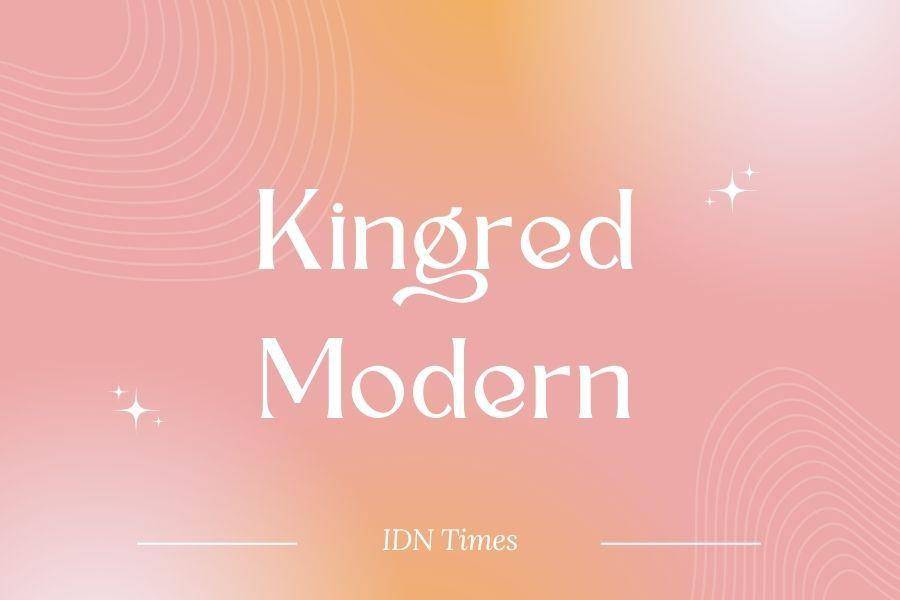
ilustrasi font Canva (dok. Canva) Mencari tulisan yang cocok untuk heading, tapi ada sentuhan artistik? Kingred Modern bisa jadi pilihan pas. Font ini memiliki lekukan ala vintage dengan basis serif.
Font ini cocok digunakan ketika kamu sedang membuat desain yang klasik. Gak membosankan, tapi tetap bisa terbaca dengan jelas.
2. Signature
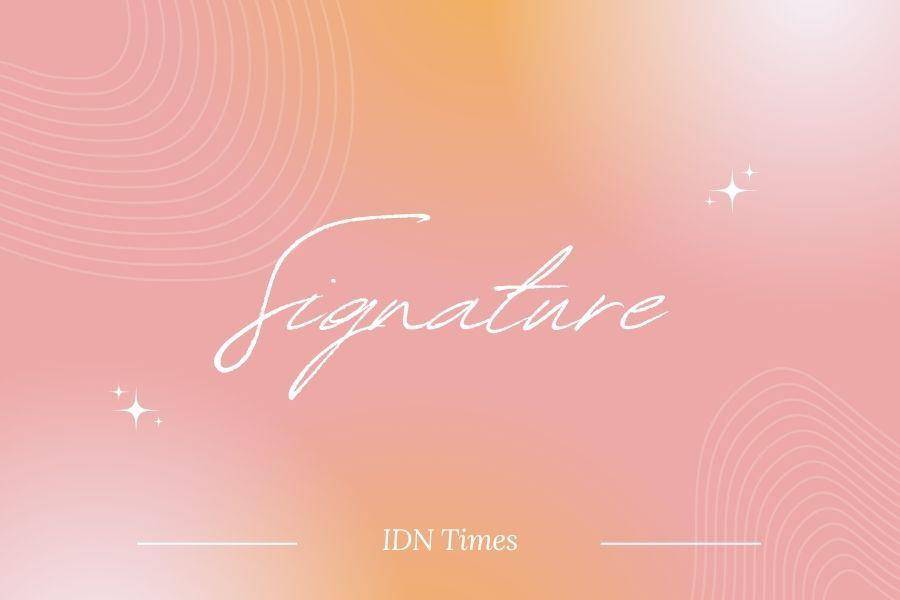
ilustrasi font Canva (dok. Canva) Font Canva yang bagus untuk desain dan slide presentasi berikutnya ada Signature. Sesuai namanya, font ini seperti handwritten yang menyerupai tanda tangan.
Signature mungkin tidak terlalu jelas terbaca jika digunakan untuk font head atau judul. Namun, font ini sangat cocok menjadi highlight dan dikombinasikan dengan font geometris dalam kontenmu.
3. Balgin
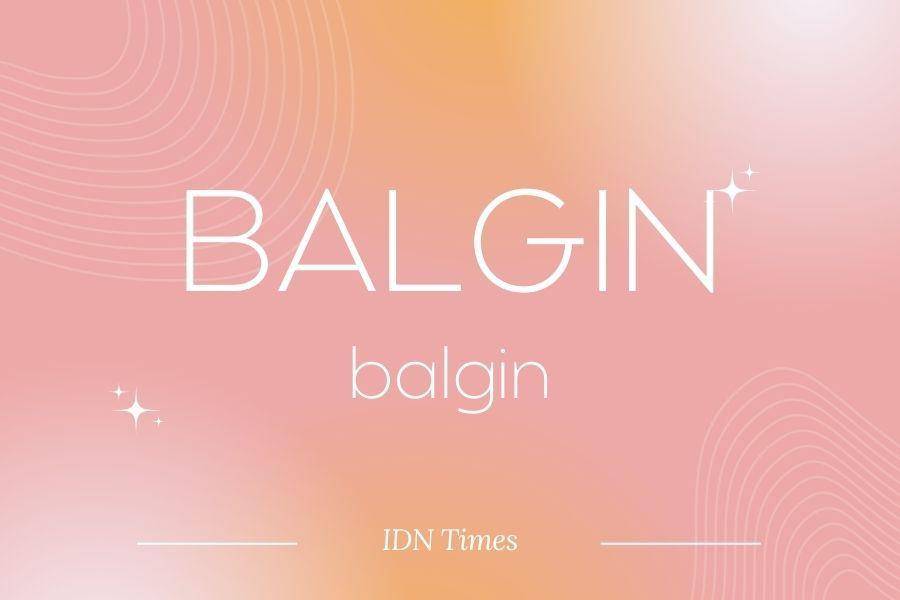
ilustrasi font Canva (dok. Canva) Mencari font Canva yang bagus dan tegas, tanpa harus memberikan penekanan? Gunakan font Balgin untuk atensi utama dalam desainmu. Meski terkesan masif, font ini gak memberikan aksen intimidatif.
Huruf ini menggunakan garis tajam dan struktur yang bersih. Pas juga digunakan untuk sentuhan retro. Desainmu pun makin estetik dan jelas.
4. Tan Meringue
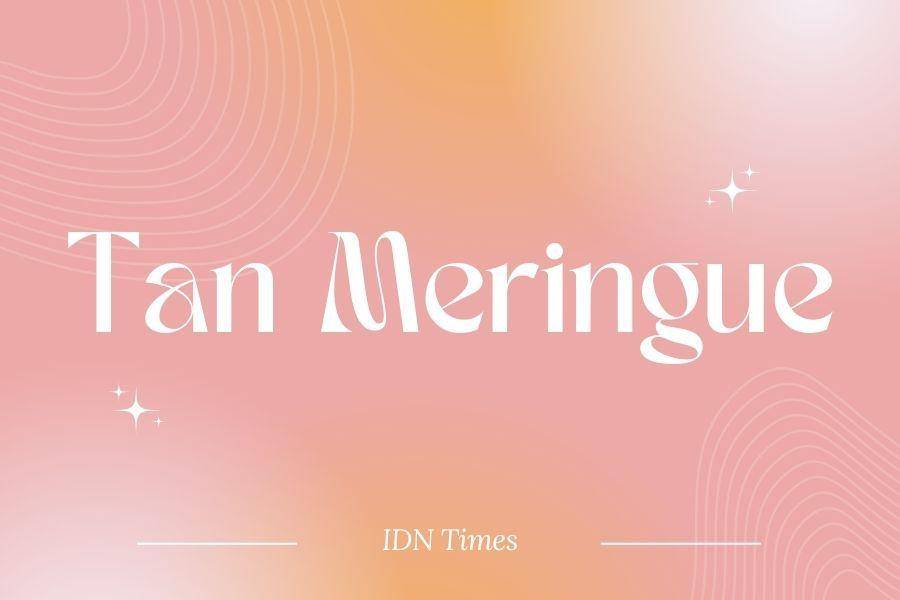
ilustrasi font Canva (dok. Canva) Tan Meringue merupakan font yang dibuat oleh tim kreatif TanType. Mengusung konsep retro, karakter dari font ini memiliki sentuhan yang gak sepenuhnya kaku, tapi tetap mudah dibaca.
Font ini mendukung huruf kapital maupun huruf kecil. Kombinasi keduanya pun tetap menghasilkan display tulisan yang aesthetic.
5. Gistesy
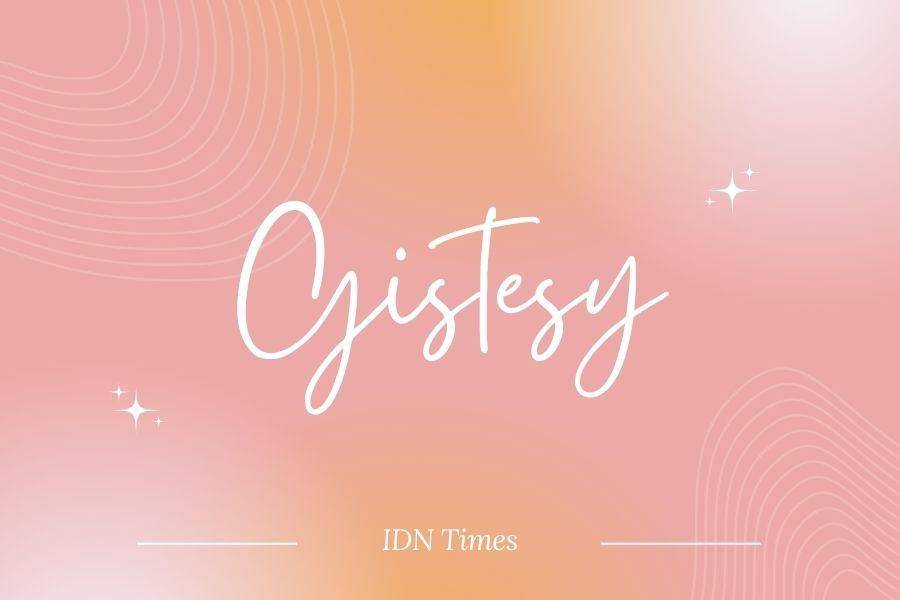
ilustrasi font Canva (dok. Canva) Gistesy merupakan handwritten font yang menampilkan kesan ceria. Meski merupakan huruf bersambung, fon ini masih tetap mudah terbaca. Cocok untuk dibuat heading maupun highlight tambahan di desainmu.
Fon ini tetap cocok berdiri sendiri, jika konsep desainnya informal. Kamu pun bisa memadukannya dengan huruf geometris jika digunakan sebagai aksen tambahan.
6. Julius Sans One
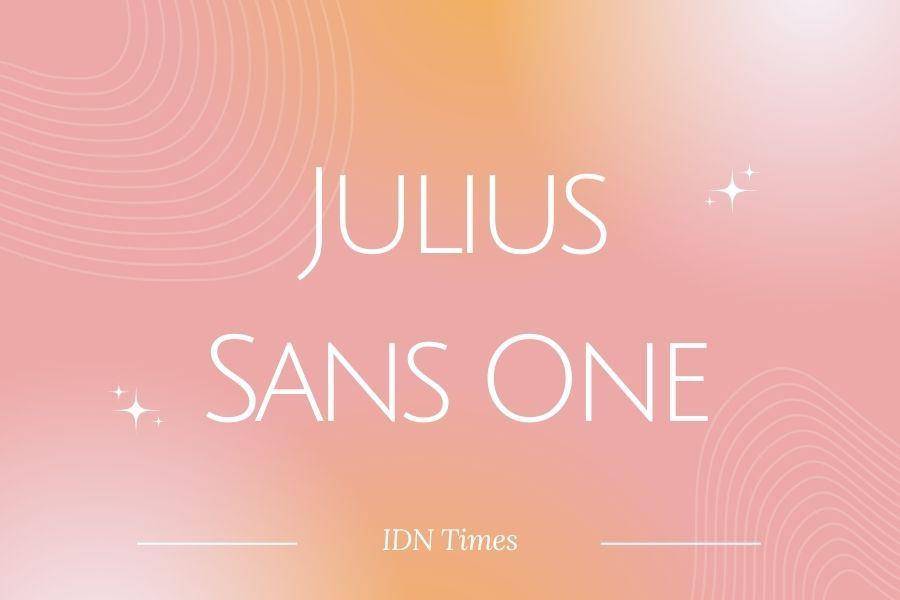
Mencari font Canva yang bagus untuk desain, slide presentasi, bahkan untuk desain branding merekmu? Julius Sans One merupakan satu fon yang bisa all in one. Modelnya sederhana, tetapi gak membosankan.
Kamu pun dapat mengatur tingkat kerapatan antar huruf. Memberikan kesan tegas, mudah terbaca, tanpa harus terkesan kaku.
7. Hatton
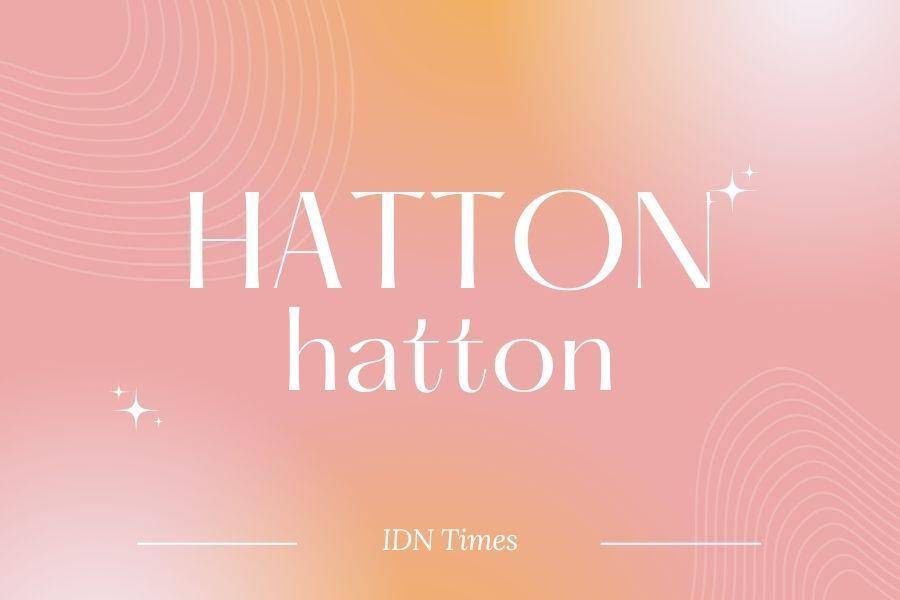
Font Canva yang bagus untuk desain sampai slide presentasi berikutnya bernama Hatton. Fon ini termasuk jenis huruf kaligrafi. Perancangnya adalah Mathieu Desjardins yang bekerja sama dengan studio desain Two Times Elliott.
FYI, desain font ini terinspirasi dari rambu jalan dan bagian depan toko listrik di distrik Hatton Garden, London. Kamu bisa menggunakannya sebagai huruf kapital dengan aksen maupun huruf kecil.
8. Sego
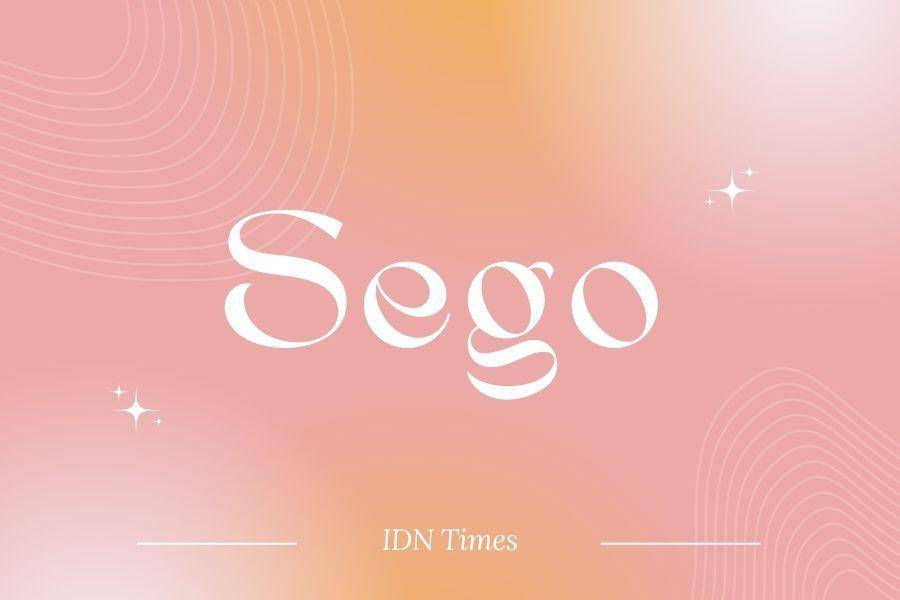
Font Sego merupakan bentuk huruf serif dengan sentuhan elegan dan modern. Tiap hurufnya memiliki akses dan lekukan yang berbeda. Bukan hanya itu, ada beberapa font alternatif yang bisa bikin desain makin ciamik.
Bentuk font yang menarik, membuatnya cocok diaplikasikan untuk banyak hal. Karakter yang dibangun dari font ini pun kuat sehingga membuat desain tampak lebih hidup.
9. Josephine Sans
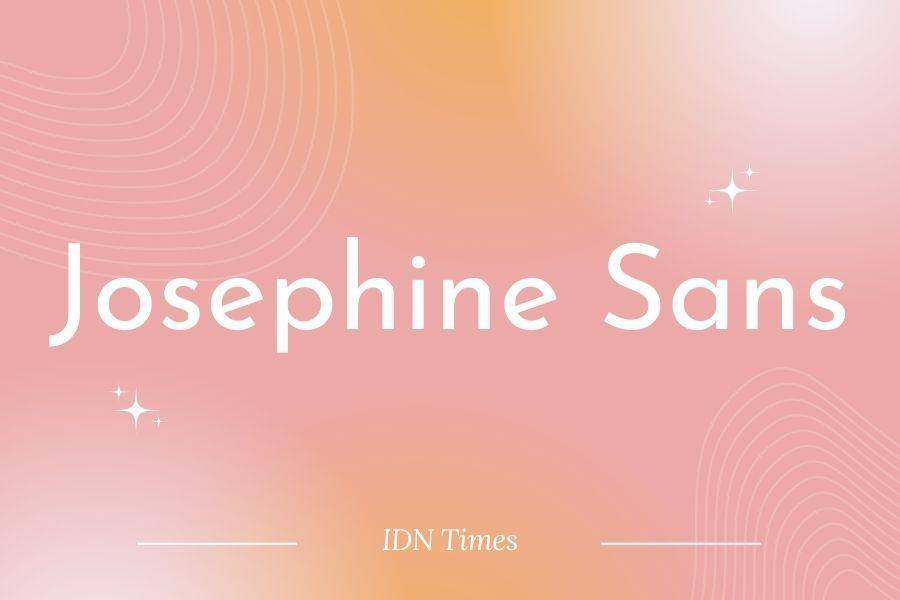
Satu tantangan membuat desain adalah menemukan font Canva yang bagus bukan hanya untuk judul, tapi juga body text. Nah, Josephine Sans ini termasuk yang bisa keduanya.
Terinspirasi dari desain sans-serif geometris tahun 1920-an, tinggi titik x dari fon ini berada di tengah-tengah. Membuat proporsinya tampak menarik dan mudah dibaca.
10. Libre Baskerville
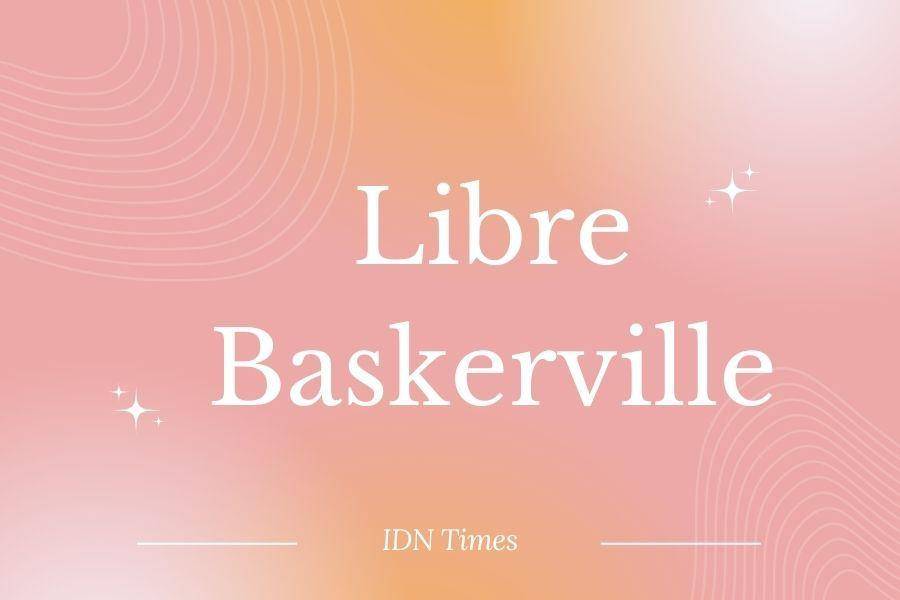
Libre Baskerville merupakan fon modern dan bergaya yang dapat digunakan untuk berbagai desain berbeda. Mau dibuat untuk judul, cocok. Dibuat body text pun tetap terbaca dengan jelas.
Font ini cocok digunakan untuk menambahkan kesan formal, tapi gak terlalu kaku. Masih match juga kalau dikombinasikan dengan fon geometri yang estetik.